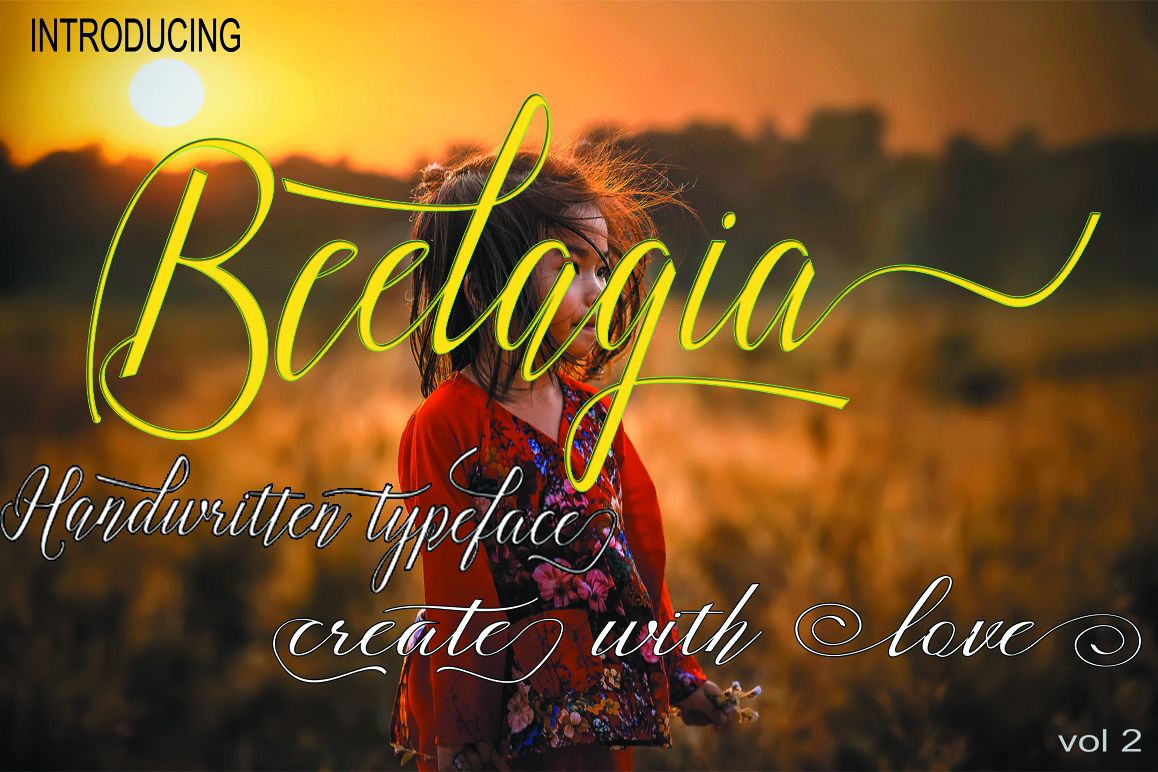
Beelagia
Beelagia Script adalah skrip yang segar dan modern dengan gaya kaligrafi buatan tangan. Ini fitur karakter dekoratif dan tarian dasar! Ini bagus untuk banyak kegunaan, seperti undangan, kartu ucapan, materi branding, kartu nama, tanda kutip & poster, surat surat dan banyak lagi. Ini dikemas dengan mesin 483 terbang. File lengkap: Beelagia. (Otf, ttf) Untuk mendukung alternatif. Yang lebih baru. Ada cara tambahan untuk mengakses alternatif / swash, menggunakan Character Map (Windows), Nexus Font (Windows), Font Book (Mac) atau program perangkat lunak seperti PopChar (untuk Windows dan Mac).